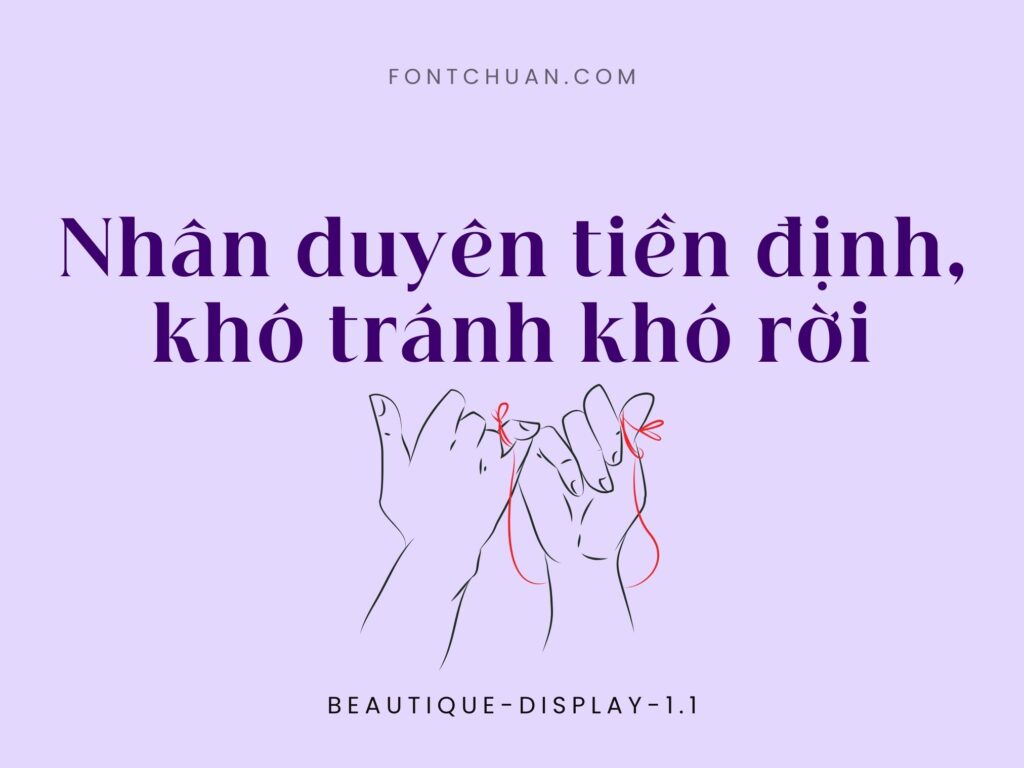
Font Beautique Display 1.1 Font Tiếng Việt
Tác giả Font: Beautype Studio
Việt hóa bởi: Beautype Studio
Beautique Display là một font chữ serif độc quyền được thiết kế bởi BeauType Studio, lấy cảm hứng từ nghệ thuật thư pháp cổ điển, đặc biệt là kiểu chữ La Mã. Font này kết hợp giữa sự thanh lịch của thư pháp truyền thống và các yếu tố thiết kế hiện đại, tạo nên một kiểu chữ độc đáo và cuốn hút. Beautique Display hỗ trợ đầy đủ tiếng Việt và nhiều ngôn ngữ khác, được sưu tầm và đăng bởi thành viên của Font Chuẩn.
Font có thiết kế với các đường cong mềm mại và độ tương phản cao giữa các nét chữ, tạo nên sự cân bằng giữa tính nữ tính và nam tính. Beautique Display phù hợp cho các thiết kế như thiệp mời, logo, tiêu đề và các ấn phẩm truyền thông cần sự sang trọng và chuyên nghiệp. Các ngành nghề như quảng cáo, thiệp cưới, giáo dục và ẩm thực có thể tận dụng hiệu quả font này. Ngoài ra, Beautique Display cũng thích hợp cho các sự kiện như lễ hội, sinh nhật, ngày Nhà giáo và Valentine.